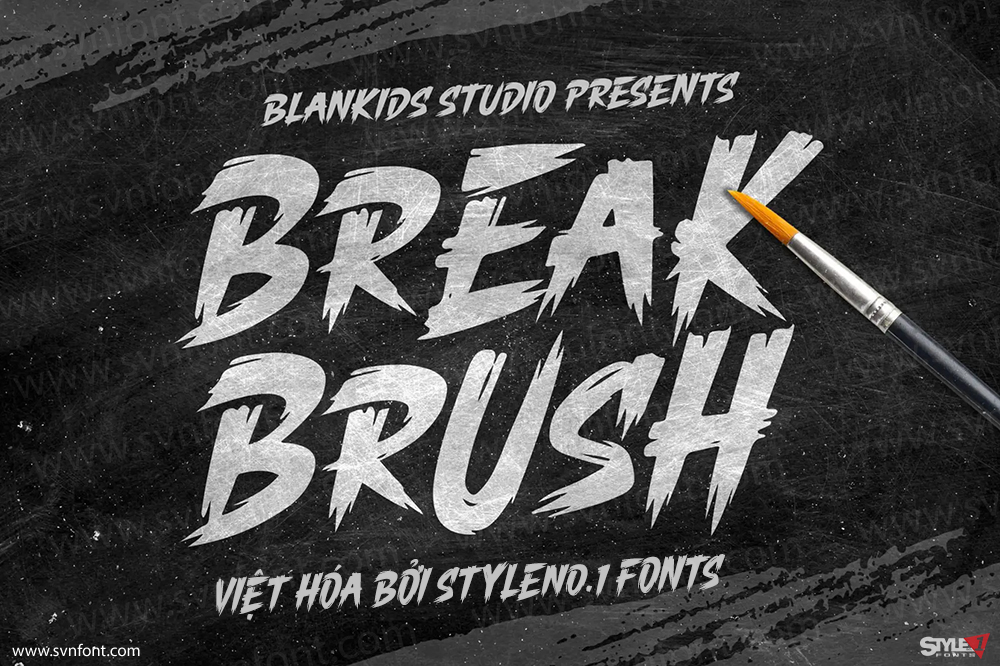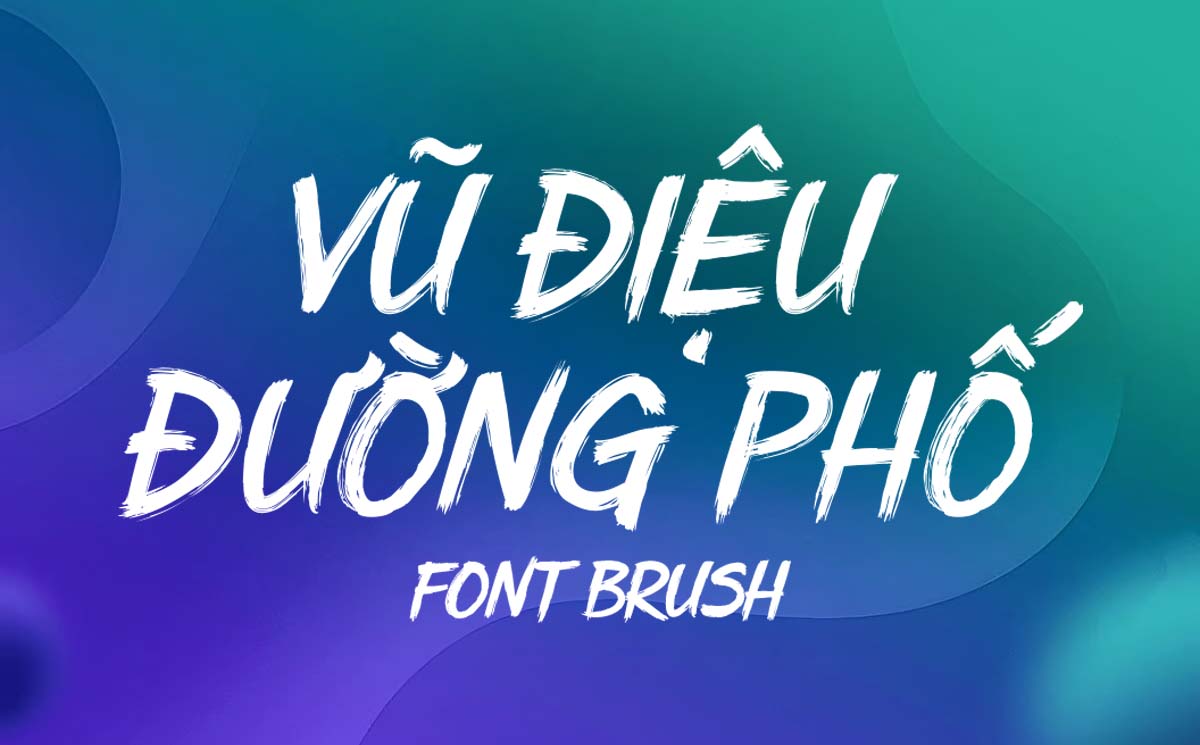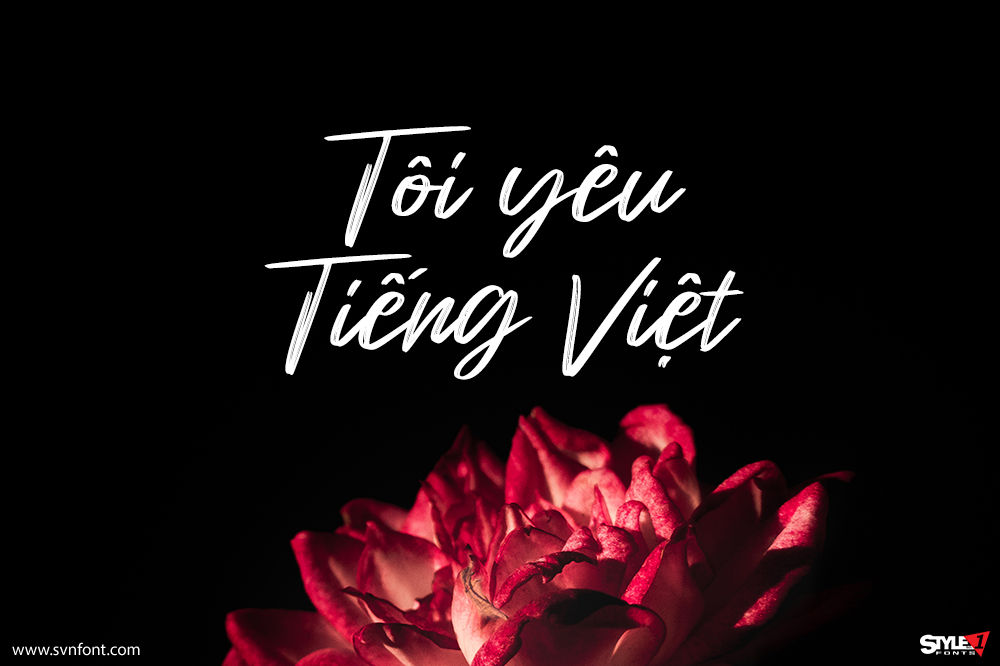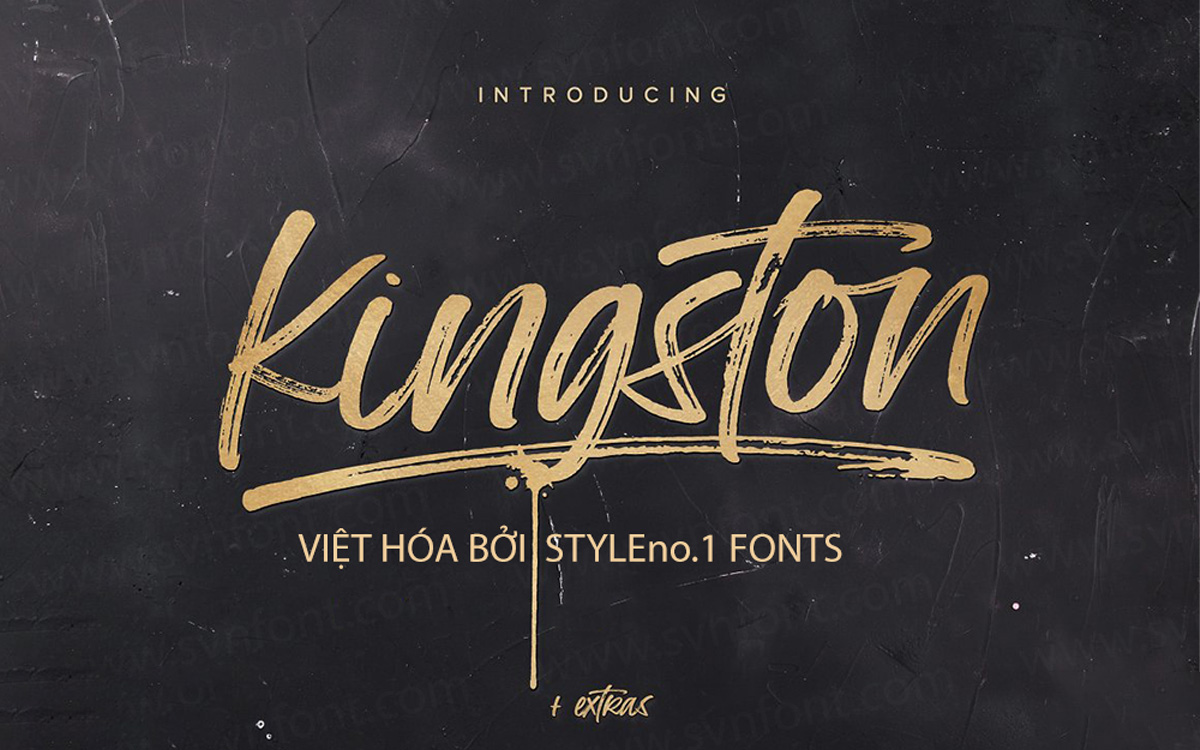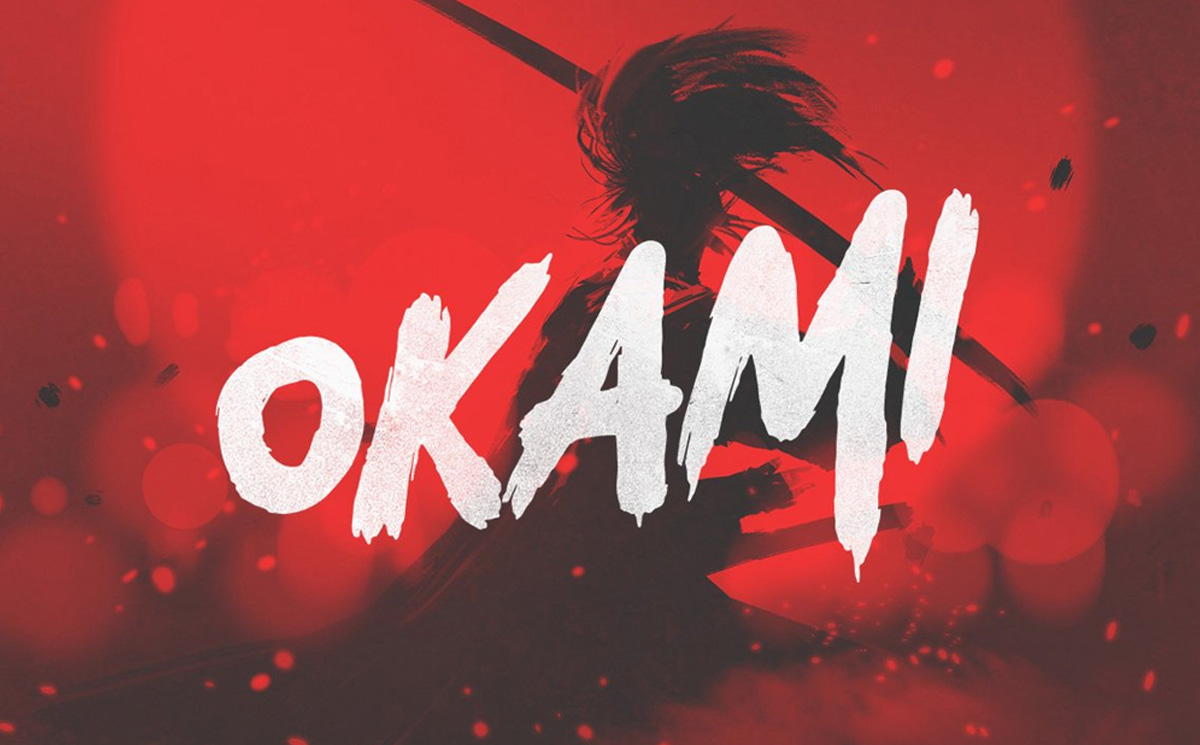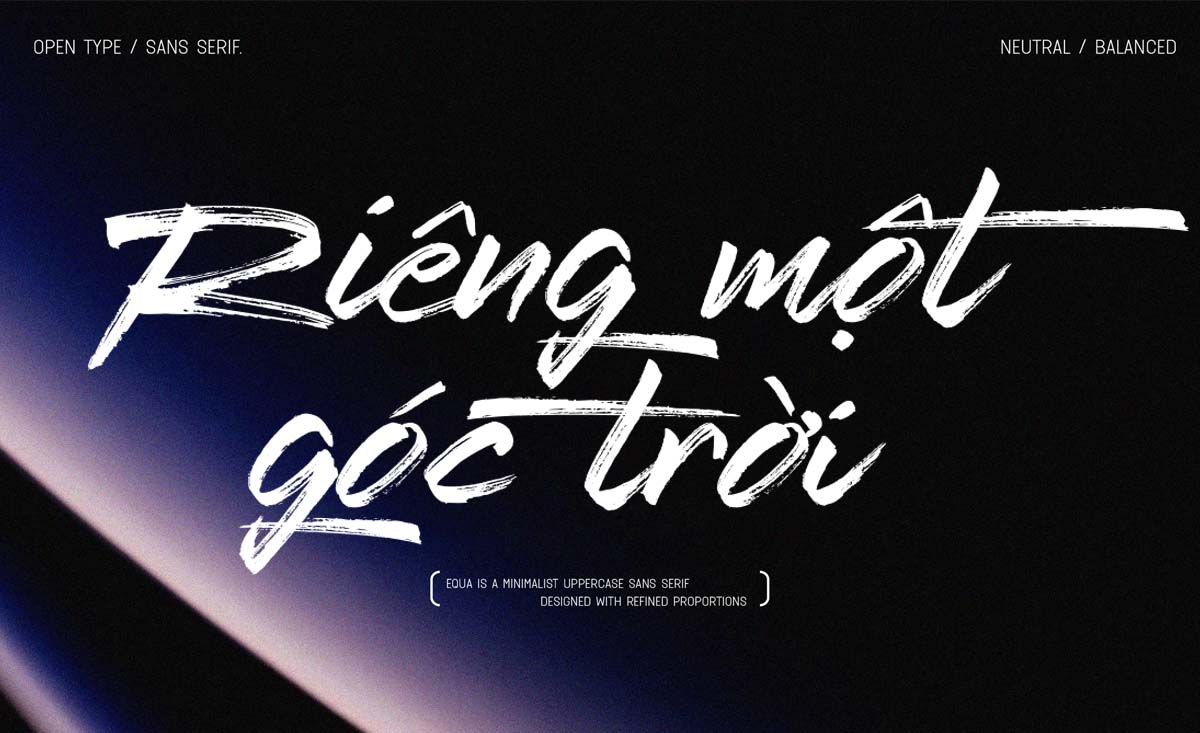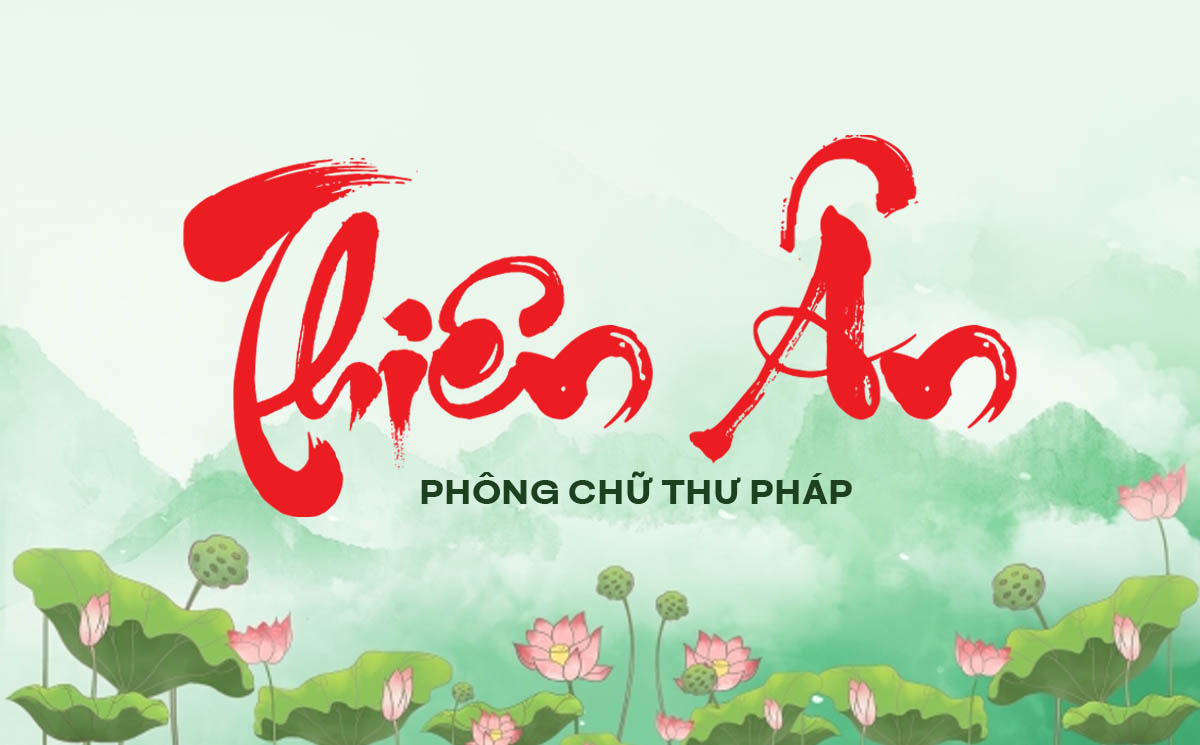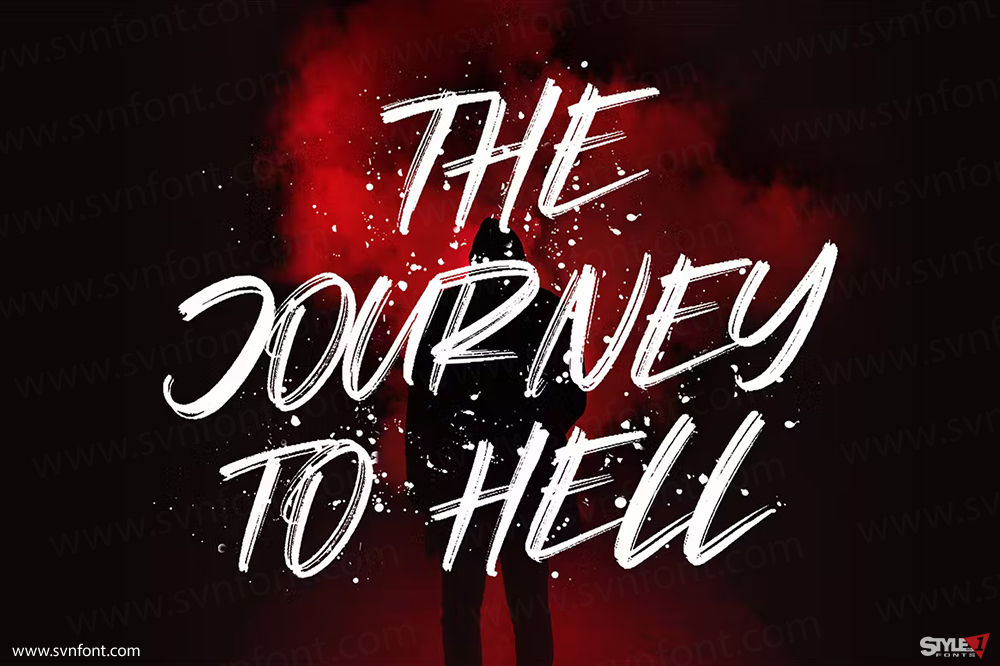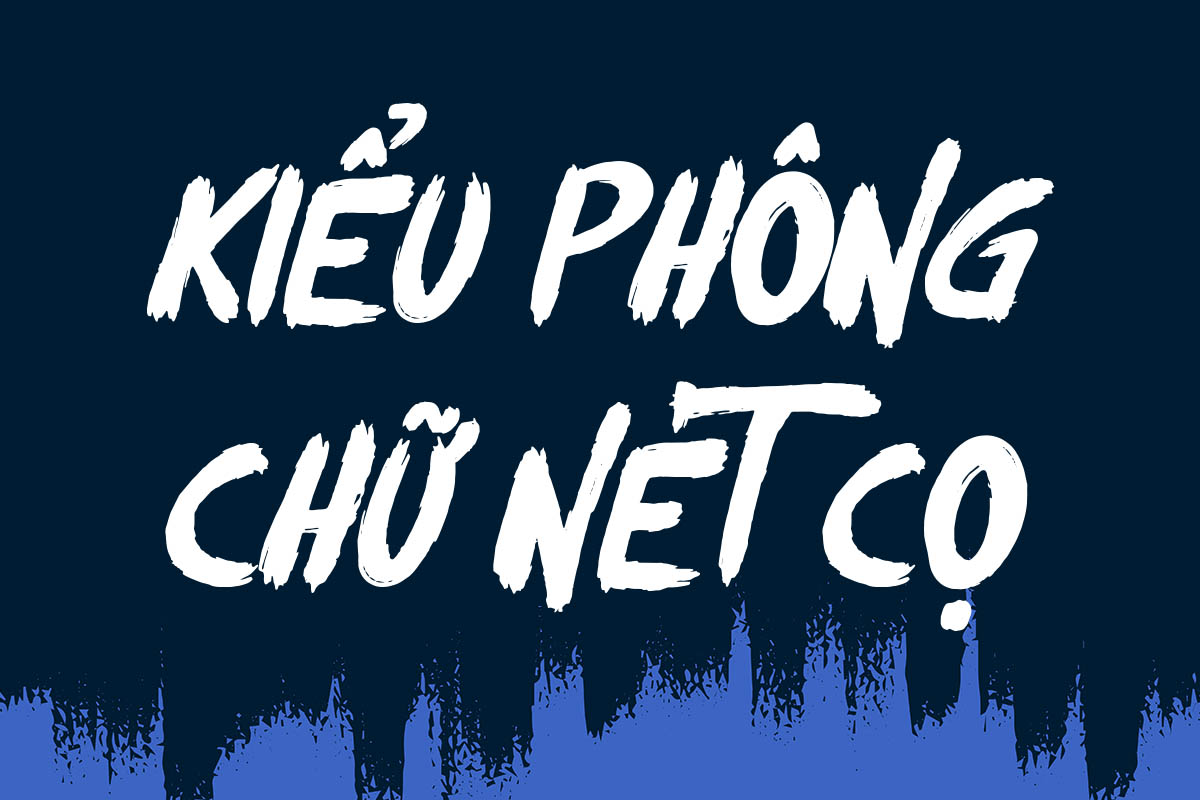
Tổng Hợp 15 Font Chữ Nét Cọ Việt Hóa Đẹp Nhất 2025
Khám phá 15 font chữ nét cọ Việt hóa đẹp nhất 2025, mang phong cách nghệ thuật, thư pháp, đường phố, hiện đại và đầy cảm xúc – tải miễn phí tại Fontdep.vn.
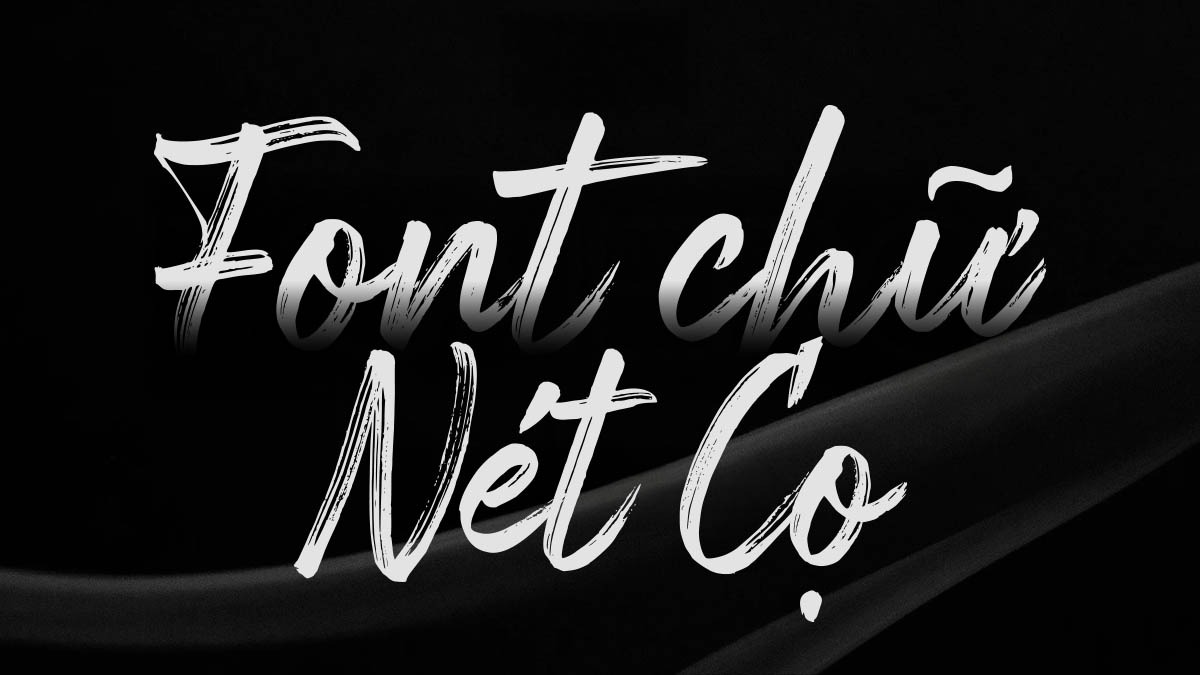
Trong thiết kế hiện đại, font chữ nét cọ (brush font) là lựa chọn lý tưởng để thể hiện cá tính, cảm xúc và dấu ấn nghệ thuật riêng. Với đường nét vẽ tay sống động, mạnh mẽ hoặc uyển chuyển, những font chữ này giúp thiết kế trở nên sinh động, cuốn hút ngay từ cái nhìn đầu tiên.
Đặc biệt, các font chữ nét cọ Việt hóa ngày càng được ưa chuộng nhờ hỗ trợ đầy đủ tiếng Việt, dễ ứng dụng và phù hợp với nhiều mục đích sáng tạo. Cùng Fontdep.vn khám phá 15 font nét cọ ấn tượng nhất 2025 – sẵn sàng để bạn tải về và sử dụng ngay trong dự án của mình!
Font chữ nét cọ là gì?
Font chữ nét cọ (brush font) là kiểu chữ được thiết kế mô phỏng nét vẽ tay bằng cọ – có thể là cọ sơn, bút mực hoặc cọ thư pháp. Đặc trưng của font này thường bao gồm:
- Đường nét không đồng đều, có cảm giác viết tay thật.
- Hiệu ứng texture như mực loang, nét gãy, cọ quét tự nhiên.
- Truyền tải cảm xúc mạnh mẽ, mang đậm chất nghệ thuật hoặc cá tính nổi bật.
Khác với các font viết tay đều nét hoặc dạng chữ nghiêm chỉnh, font chữ nét cọ thường “phóng khoáng” hơn – rất phù hợp với các thiết kế mang tính biểu cảm cao như typography, poster nghệ thuật, tiêu đề phim, logo cá nhân hoặc các dự án sáng tạo mang phong cách đường phố.
Khi nào nên dùng font chữ nét cọ?
Font chữ nét cọ không chỉ đẹp về mặt hình thức mà còn cực kỳ linh hoạt trong ứng dụng thực tế. Với khả năng truyền tải cảm xúc mạnh mẽ, tự nhiên và đầy cá tính, kiểu chữ này rất phù hợp trong các tình huống cần gây ấn tượng thị giác hoặc thể hiện cái tôi sáng tạo. Bạn có thể sử dụng phông chữ nét cọ trong các thiết kế như:
- Poster nghệ thuật, banner phim hành động, bìa chương trình âm nhạc.
- Tiêu đề video, ảnh bìa YouTube hoặc bài đăng nổi bật trên mạng xã hội.
- Bao bì sản phẩm thủ công, mỹ phẩm thiên nhiên, đồ lưu niệm hoặc quà tặng cá nhân.
- Typography trang trí, trích dẫn truyền cảm hứng, in ấn sáng tạo cá nhân hóa.
- Logo cá nhân hoặc thương hiệu nhỏ cần sự gần gũi và độc đáo.
Bất cứ khi nào bạn muốn mang đến một cảm giác “tay viết thật”, chân thành và sinh động, font chữ nét cọ luôn là lựa chọn không bao giờ nhàm chán.
Top 15 Font Chữ Nét Cọ Việt Hóa Đẹp Nhất 2025
1. Font chữ nét cọ thư pháp Đức Thủy mang hồn Việt truyền thống
Font Đức Thủy mang phong cách thư pháp cách điệu, với các nét cọ kéo dài, cong lượn đầy uyển chuyển và dứt khoát. Kiểu chữ tạo nên sự kết hợp hài hòa giữa truyền thống và hiện đại, gợi nhớ đến bản sắc văn hóa Việt Nam trong các tác phẩm thư họa. Nét chữ to, chắc tay nhưng không cứng nhắc, dễ dàng thu hút ánh nhìn và tạo điểm nhấn cho các thiết kế cần tính nghệ thuật cao như poster Tết, thiệp chúc mừng, hay các ấn phẩm văn hóa.
2. Font chữ nét cọ hiện đại SVN Drainwood mềm mại và tinh tế
SVN Drainwood sở hữu phong cách brush script hiện đại, với các nét chữ kéo dài mềm mại như những dòng mực chảy tự do trên giấy. Các ký tự có độ nghiêng nhẹ, phần đầu và cuối nét thường được xử lý vát nhọn tạo cảm giác thanh thoát nhưng vẫn giữ được sự chắc chắn. Font đặc biệt phù hợp trong các thiết kế cần yếu tố cá nhân như logo mỹ phẩm, bìa sách sáng tạo hoặc lời trích dẫn trên nền ảnh.
3. Font chữ nét cọ Nhật Bản SVN Hiro Misake cá tính và mạnh mẽ
SVN Hiro Misake gây ấn tượng với đường nét dày dặn, vuông vức và có đầu cọ xước nhẹ ở cuối mỗi ký tự, tạo cảm giác như được viết nhanh bằng cọ lông Nhật Bản. Font sở hữu sự chắc chắn trong cấu trúc nhưng vẫn giữ được vẻ tự nhiên đặc trưng của nét cọ viết tay. Với lối trình bày cân đối và dễ đọc, font đặc biệt phù hợp cho các thiết kế liên quan đến văn hóa Nhật Bản, poster anime, tiêu đề truyện tranh hoặc các dự án mang tinh thần phương Đông hiện đại.
- Tác giả gốc: Edric Studio
- Việt hóa bởi: STYLEno.1 Fonts
4. Font chữ nét cọ đường phố SVN Dexsar Brush phóng khoáng và nổi bật
SVN Dexsar Brush mang đậm tinh thần đường phố với những nét cọ dày, thô ráp và không đồng đều, tạo cảm giác như được viết vội bằng sơn trên tường hoặc bảng hiệu tạm. Các ký tự xen kẽ giữa nét đậm và khoảng trống loang lổ giúp font giữ được vẻ sống động và phá cách. Font này rất thích hợp cho những thiết kế cần truyền tải năng lượng như poster hiphop, banner sự kiện, bìa album cá tính hoặc các sản phẩm hướng đến giới trẻ.
- Tác giả gốc: Dirtyline Studio
- Việt hóa bởi: STYLEno.1 Fonts
5. Font chữ nét cọ mạnh mẽ SVN Okami – đậm chất hành động
SVN Okami mang vẻ ngoài táo bạo với những nét cọ thô ráp, sần sùi và dứt khoát như được vung mạnh bằng cọ lông to. Mỗi ký tự hiện lên như một vết chém thị giác, mang đến cảm giác đầy kịch tính và ám ảnh – phù hợp tuyệt đối với các thiết kế lấy cảm hứng từ samurai, hành động hoặc thế giới hậu tận thế. Sự bất cân xứng giữa các nét tạo nên chất riêng cho font, khiến nó trở thành lựa chọn hàng đầu cho tiêu đề poster phim, game phiêu lưu hoặc sản phẩm cần tạo dấu ấn mạnh mẽ.
- Tác giả gốc: Tugcu Design Co.
- Việt hóa bởi: STYLEno.1 Fonts
- Tải về: SVN Okami
6. Font chữ nét cọ mềm mại TH Kinetic Motion lãng mạn và nhẹ nhàng
Kinetic Motion mang phong cách chữ viết tay hiện đại với đường nét uyển chuyển, đều đặn và mềm mại như một dòng chảy êm đềm. Các ký tự được bo tròn vừa phải, kết hợp với những nét nối mảnh ở phần đuôi chữ tạo nên cảm giác nhẹ nhàng, thư giãn. Font tạo nên một không khí ngọt ngào, rất lý tưởng cho các thiết kế mang thông điệp tích cực như poster mùa hè, thiệp chúc mừng, bìa sách thiếu nhi hay hình ảnh mạng xã hội mang cảm xúc cá nhân.
- Tác giả gốc: Letterena
- Việt hóa bởi: Phạm Sơn - Admin S99, Fontdep.vn
- Tải về: TH Kinetic Motion
7. Font chữ nét cọ viết tay TH Maryatha thanh lịch và tinh tế
TH Maryatha là kiểu chữ viết tay dạng script với đường nét uốn lượn mềm mại, được tô điểm bằng các chi tiết bay bổng ở phần đầu và đuôi mỗi ký tự. Texture mô phỏng nét phấn hoặc bút chì mang đến cảm giác gần gũi và có phần hoài niệm, tạo nên một tổng thể hài hòa giữa nghệ thuật thủ công và sự chỉnh chu hiện đại. Font cực kỳ phù hợp cho các thiết kế nữ tính như logo thương hiệu cá nhân, thiệp cưới, typography trang trí hoặc bìa sách tình cảm.
- Việt hóa bởi: Phạm Sơn
- Tải về: TH Maryatha
8. Font chữ nét cọ bay bổng SVN Maghrib đầy cảm hứng sáng tạo
Maghrib gây ấn tượng với kiểu chữ script cọ hiện đại, các nét uốn lượn mềm mại kết hợp cùng độ dày vừa phải tạo nên sự cân đối và đầy sức sống. Những đường kéo dài ở đầu hoặc cuối chữ mang đến cảm giác chuyển động liên tục, như một cánh chim đang lướt qua bầu trời rộng. Font này là lựa chọn lý tưởng cho các thiết kế cần truyền tải sự tự do, khát vọng và năng lượng tích cực như poster truyền cảm hứng, tiêu đề video hoặc dự án cá nhân mang thông điệp bay xa.
- Tác giả gốc: Afkari Studio
- Việt hóa bởi: STYLEno.1 Fonts
- Tải về: SVN Maghrib
9. Font chữ nét cọ thư pháp Đại Tự cổ điển và trang trọng
Thư Pháp Đại Tự gợi lên tinh thần Việt Nam đậm nét với những đường cọ lớn, dày bản và bố cục chữ mang tính trang trọng. Mỗi ký tự được thiết kế tỉ mỉ với phần đầu vung tay mạnh, phần kết gọn gàng, tạo cảm giác như đang ngắm một bức thư pháp viết bằng mực tàu truyền thống trên nền giấy dó. Phông chữ này rất thích hợp cho các thiết kế mang yếu tố truyền thống như câu đối, tranh thư pháp, bìa sách Hán Nôm hoặc các ấn phẩm văn hóa cần sự uy nghi và tôn kính.
- Tác giả gốc: Đức Thủy Admin FontZin
- Việt hóa bởi: Đức Thủy Admin FontZin
- Tải về: Thư Pháp Đại Tự
10. Font chữ nét cọ truyền thống UTM Thien An tĩnh tại và sâu lắng
UTM Thien An mang đậm tinh thần thư pháp Việt với những nét cọ mạnh tay, sắc sảo và có chiều sâu. Các ký tự được thiết kế với độ loang mực rõ nét, tạo hiệu ứng thị giác như vừa được viết bằng bút lông trên giấy xuyến chỉ. Sự chắt lọc trong từng đường nét giúp font vừa giữ được chất truyền thống, vừa mang lại cảm giác hiện đại. Đây là lựa chọn lý tưởng cho các thiết kế liên quan đến văn hóa phương Đông, tranh chữ, thiệp Tết, ấn phẩm tâm linh hoặc các dự án cần truyền tải thông điệp bình an và ý nghĩa sâu sắc.
- Tác giả gốc: UTM Thiên Ân
- Việt hóa bởi: UTM Team
- Tải về: UTM Thien An
11. Font chữ nét cọ phá cách SVN Break Brush dứt khoát và nổi loạn
Break Brush sở hữu kiểu dáng phá cách với các nét cọ gãy, xé và nhọn như vệt chém mạnh tay trên nền bảng vẽ. Từng ký tự được xử lý thô ráp, tạo cảm giác hỗn loạn có chủ đích, thể hiện rõ tinh thần nổi loạn, mạnh mẽ và tự do. Font mang năng lượng rất riêng, đặc biệt phù hợp cho những thiết kế đậm chất đường phố, poster hành động, tiêu đề game hoặc các ấn phẩm truyền thông cần tạo cú hích thị giác ngay từ cái nhìn đầu tiên.
- Tác giả gốc: Blankids Studio
- Việt hóa bởi: STYLEno.1 Fonts
- Tải về: Break Brush
12. Font chữ nét cọ tự nhiên SVN Break Herd mạnh mẽ và bụi bặm
Break Herd mang đậm phong cách street brush với những nét vẽ tay dài, thanh mảnh nhưng đầy sức sống. Các ký tự có cấu trúc đơn giản nhưng được điểm xuyết bằng các vệt cọ sướt mảnh, tạo cảm giác như vừa được vẽ nhanh trên tường graffiti hay một cuốn sổ phác thảo đường phố. Sự thô ráp và tự nhiên của nét chữ giúp font trở thành lựa chọn lý tưởng cho tiêu đề video, hình ảnh truyền thông cá tính, poster nghệ thuật đương đại hoặc các thiết kế đòi hỏi dấu ấn cá nhân mạnh mẽ.
- Tác giả gốc: Allouse Studio
- Việt hóa bởi: STYLEno.1 Fonts
- Tải về: Break Herd
13. Font chữ nét cọ nghệ thuật SVN Redtowns mộc mạc và tự do
Redtowns là kiểu font brush script mang tinh thần phóng khoáng với các nét vẽ tay thô, dày và có texture rõ rệt như cọ sơn vừa quét qua mặt giấy. Các ký tự được thiết kế bất đối xứng và không hoàn hảo một cách có chủ đích, tạo nên vẻ ngoài tự nhiên và có phần bụi bặm. Phong cách này giúp font thể hiện cá tính mạnh và cảm xúc thô ráp, rất phù hợp cho các thiết kế mang tính cá nhân, poster truyền cảm hứng, tiêu đề sáng tạo hoặc những dự án nghệ thuật đương đại.
- Tác giả gốc: Letterhend Studio
- Việt hóa bởi: STYLEno.1 Fonts
- Tải về: SVN Redtowns
14. Font chữ nét cọ cá tính SVN Kingston đậm chất thời trang đường phố
Kingston mang dáng vẻ của một kiểu chữ viết tay phóng khoáng với nét cọ tròn, dày và phần kéo dài đặc trưng ở chân chữ. Các ký tự được xử lý như những vệt sơn khô đang quét trên bề mặt tường thô ráp, vừa có sự tự do nghệ sĩ vừa giữ được độ ổn định trong bố cục. Font tạo hiệu ứng thị giác mạnh mẽ, rất phù hợp cho các thiết kế đậm chất cá nhân như logo thương hiệu, tiêu đề bìa sách, sản phẩm thời trang đường phố hoặc các poster quảng bá cần sự nổi bật và tinh tế.
- Tác giả gốc: Subectype Studio
- Việt hóa bởi: STYLEno.1 Fonts
- Tải về: SVN Kingston
15. Font chữ nét cọ viết tay Have Heart năng động và chân thật
Have Heart là kiểu font chữ nét cọ viết tay với các đường nét mượt, dứt khoát và đầy cảm xúc. Nét chữ mô phỏng như được tạo nên bằng cọ lông mảnh, mang lại cảm giác gần gũi, chân thực và có phần cá tính. Mỗi ký tự đều có độ nghiêng nhẹ và bố cục thoáng, tạo nên tổng thể năng động, dễ đọc và linh hoạt trong sử dụng. Font này rất phù hợp cho các thiết kế truyền cảm hứng, bài đăng mạng xã hội, typography cá nhân hoặc những dự án cần chất “người viết thật”.
- Tác giả gốc: Set Sail Studios
- Việt hóa bởi: STYLEno.1 Fonts
- Tải về: Have Heart
Cách cài đặt font chữ nét cọ nhanh chóng và đơn giản
Để sử dụng font chữ nét cọ trong thiết kế, bạn chỉ cần thực hiện vài bước đơn giản như sau:
- Tải font về dưới dạng file .zip từ các nguồn uy tín như Fontdep.vn, S99.vn…
- Giải nén file đã tải, sau đó click đúp vào tệp font (.ttf hoặc .otf) → Nhấn chọn “Cài đặt”.
- Mở phần mềm thiết kế như Photoshop, Illustrator, Canva hoặc PowerPoint → Tìm kiếm tên font để bắt đầu sử dụng.
Tiêu chí chọn font nét cọ đẹp và hiệu quả
Để lựa chọn được một font chữ nét cọ Việt hóa thực sự chất lượng và phù hợp với mục đích thiết kế, bạn có thể cân nhắc các yếu tố sau:
- Hỗ trợ tiếng Việt đầy đủ, không lỗi dấu, tương thích với đa dạng phần mềm.
- Đường nét chân thực: có texture mô phỏng cọ sơn, mực loang hoặc hiệu ứng gãy nét rõ ràng.
- Cân bằng thị giác: chữ dễ đọc, bố cục hài hòa khi kết hợp trong thiết kế.
- Phong cách linh hoạt: có thể phù hợp với nhiều tone cảm xúc – mạnh mẽ, mềm mại, thư pháp hoặc phá cách.
- Nguồn gốc rõ ràng: ưu tiên những font có thông tin tác giả và được Việt hóa uy tín.
Chỉ một font chữ nét cọ phù hợp cũng có thể làm cho thiết kế của bạn trở nên sống động, cá tính và đậm chất nghệ thuật. Dù là poster nghệ thuật, logo cá nhân hay bao bì sản phẩm, font chữ nét cọ luôn mang lại cảm xúc mạnh mẽ và không bao giờ lỗi thời.